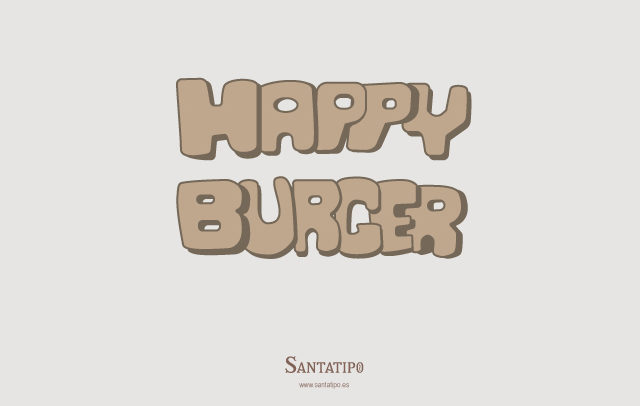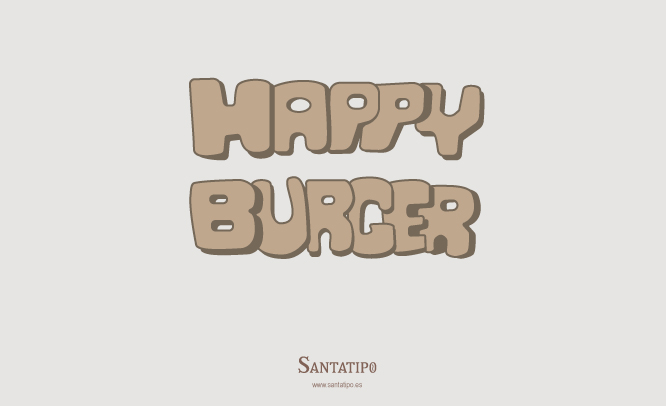
Happy Burger
Antes de la irrupción de las grandes cadenas de comida rápida y de las hamburgueserías gourmet, en Santander teníamos, al menos, tres locales míticos que nos daban la experiencia perfecta en el mundo de la Hamburguesa. El primero el EROS ROCAMAR del Sardinero, abierto en los años 70 y que cerró en 2012, fueron hamburguesas de referencia. Después FREIDURIA MANOLO en Guevara, con más de treinta años hasta el fallecimiento de Manolo, nos llenó con aquellas hamburguesas y los bocatas de Rabas; quienes vivíamos en la zona, era visita obligada con la ración de las patata de «La Mejillonera».
Y después en 1988 abrió el Happy Burger, que nos trajo el concepto de local de gran cadena, pero local. Para los que nos pilló siendo más jóvenes se convirtió en lugar de celebración de infinidad de cumpleaños y punto de encuentro en las noches. Sus letras informales rojas, con fondo blanco, era un icono en la que antes se llamaba Calle Martillo. Tras más de treinta años de actividad cerró sus puertas.